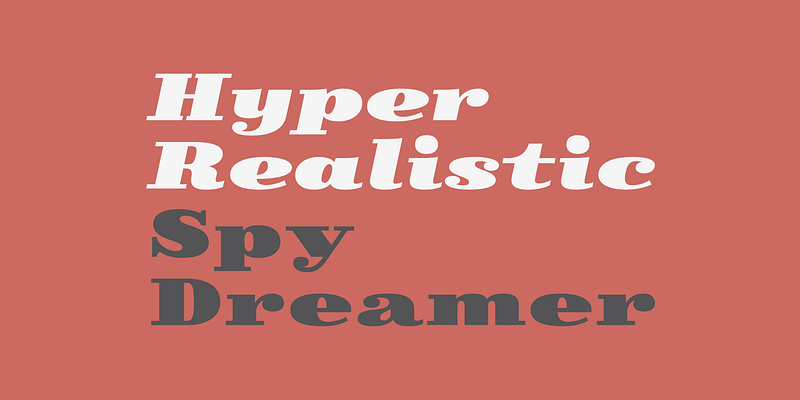
Skope ist ein Experiment in horizontaler Betonung, das an den extremen Schriftstil der Comic-Meister Josep Coll und Manuel Urda erinnert, gemischt mit den zeitgenössischen Favoriten Francesc Capdevila und Joost Swarte. Die Proportionen und grundlegenden Merkmale von Skope sind vom Impressum der Zeitschrift Triunfo (Valencia, Spanien, 1946–1982) inspiriert, und die Inspiration für die Figuren stammt von einem Foto in einem Second-Hand-Laden einer Küchenuhr aus den 1970er Jahren.